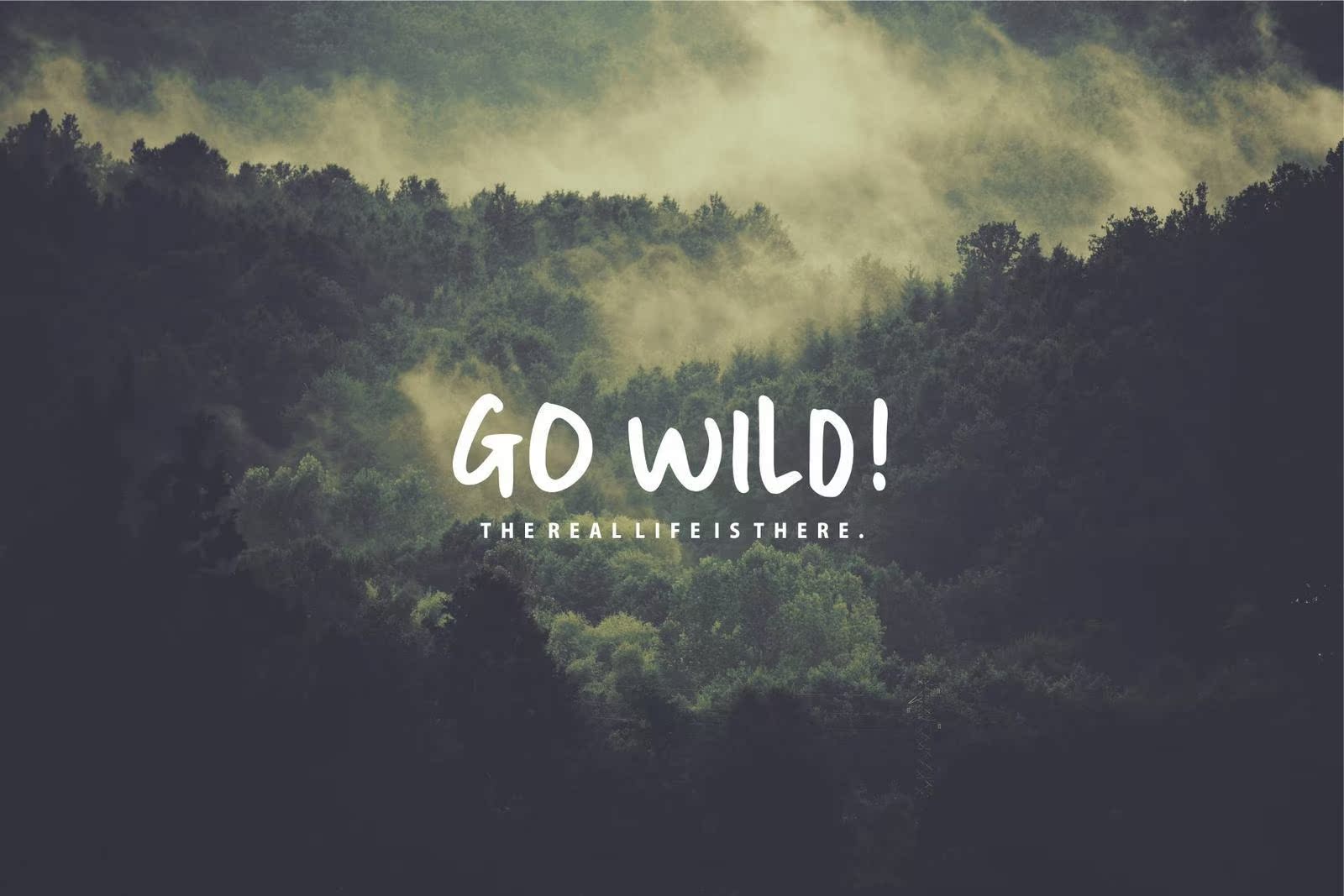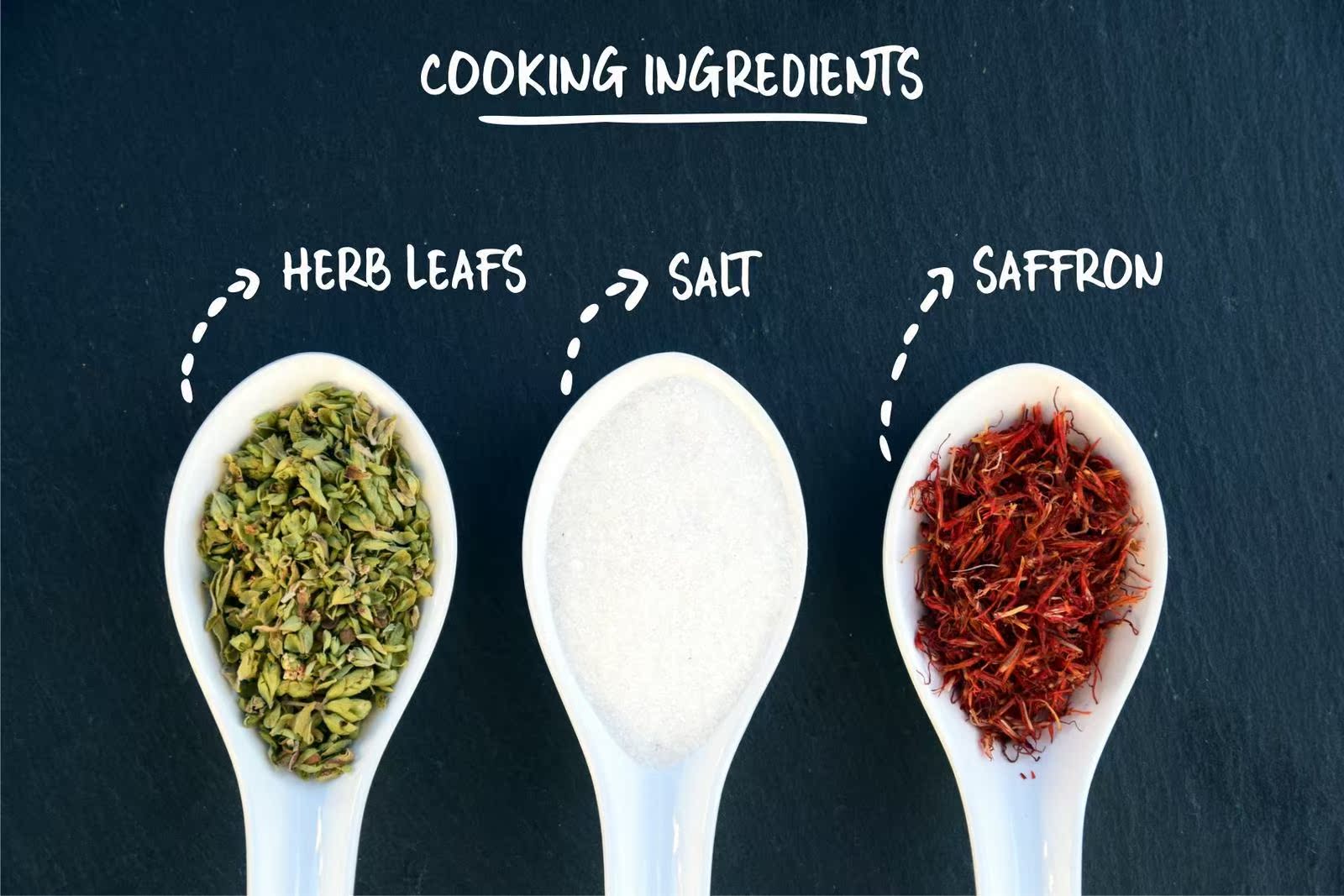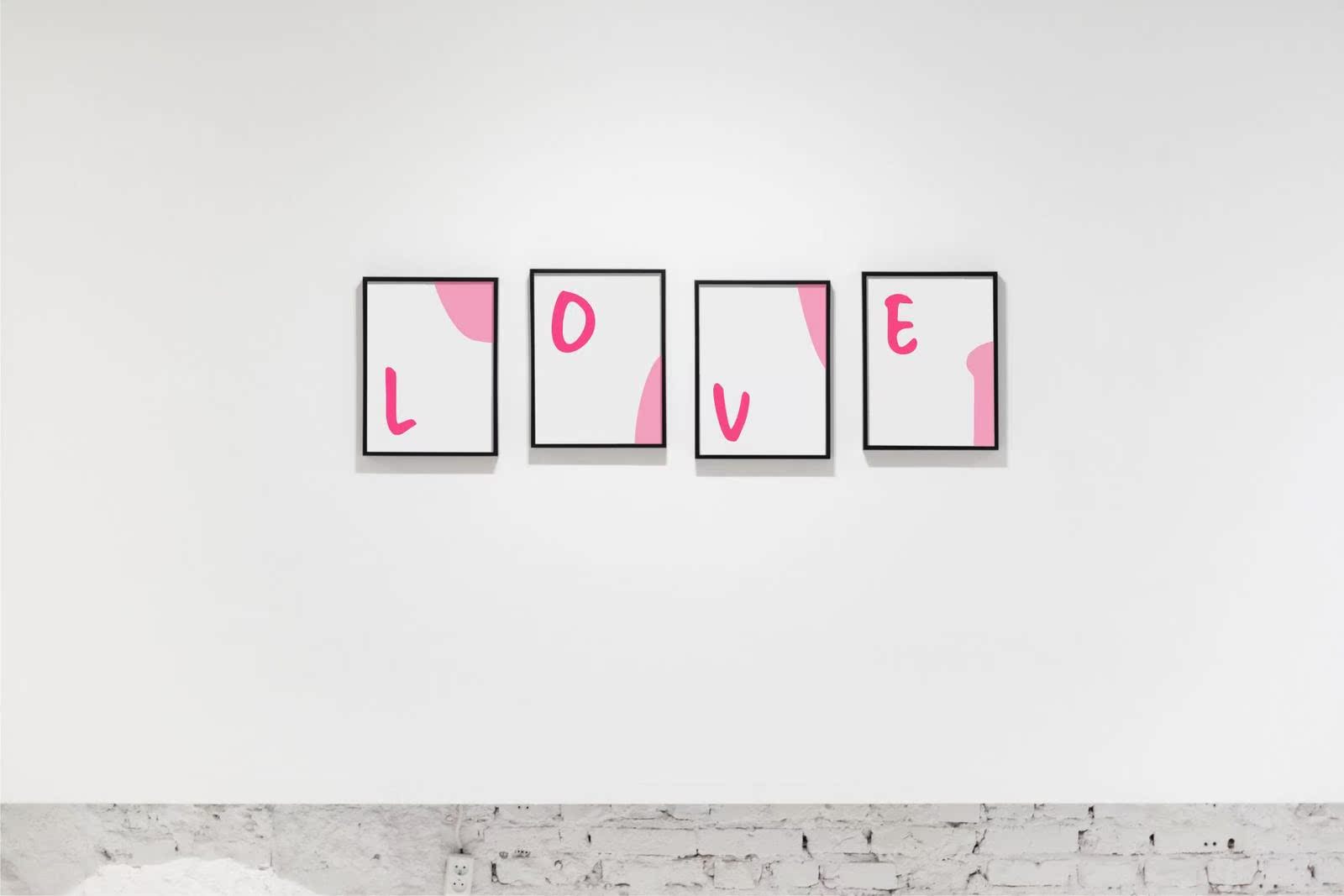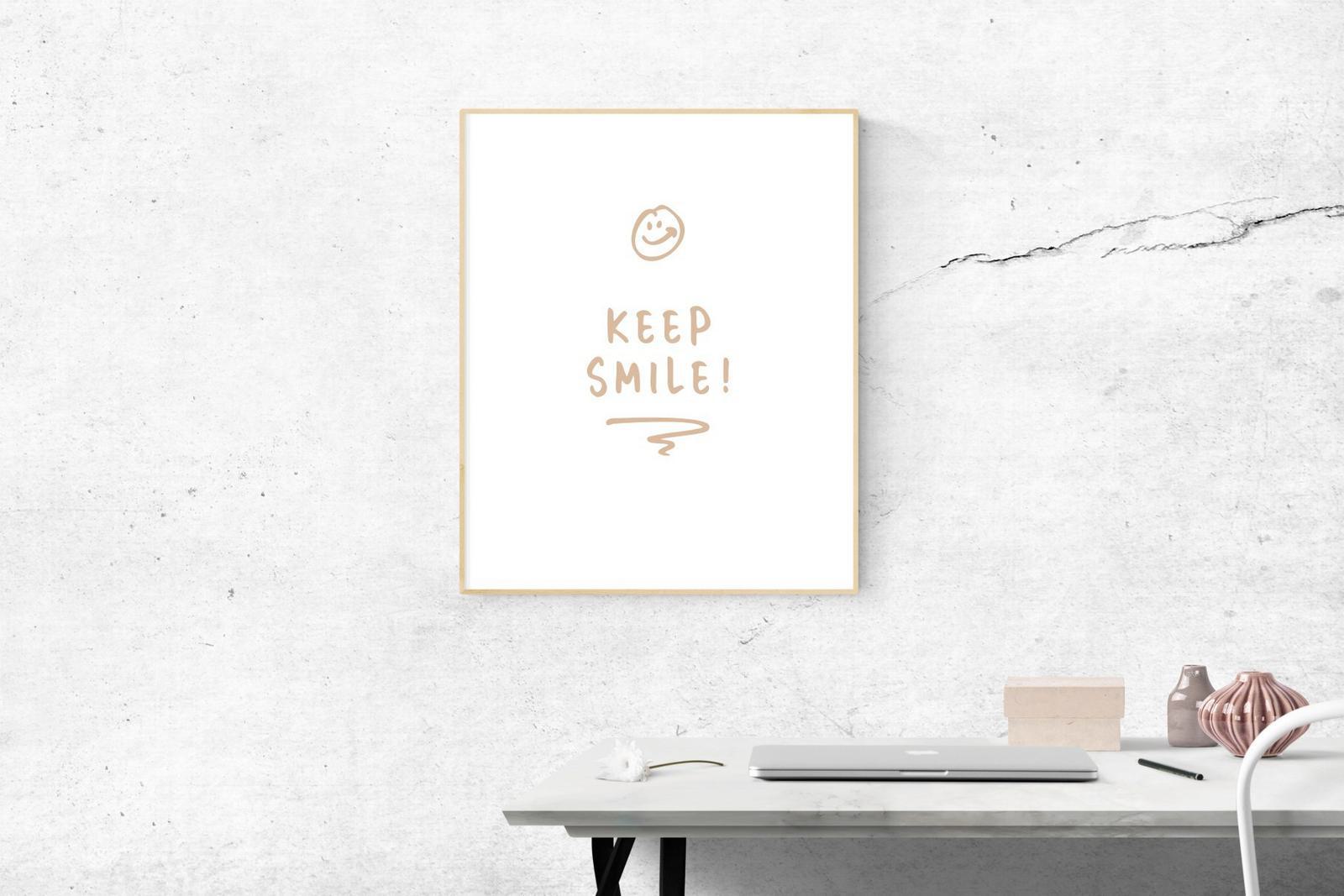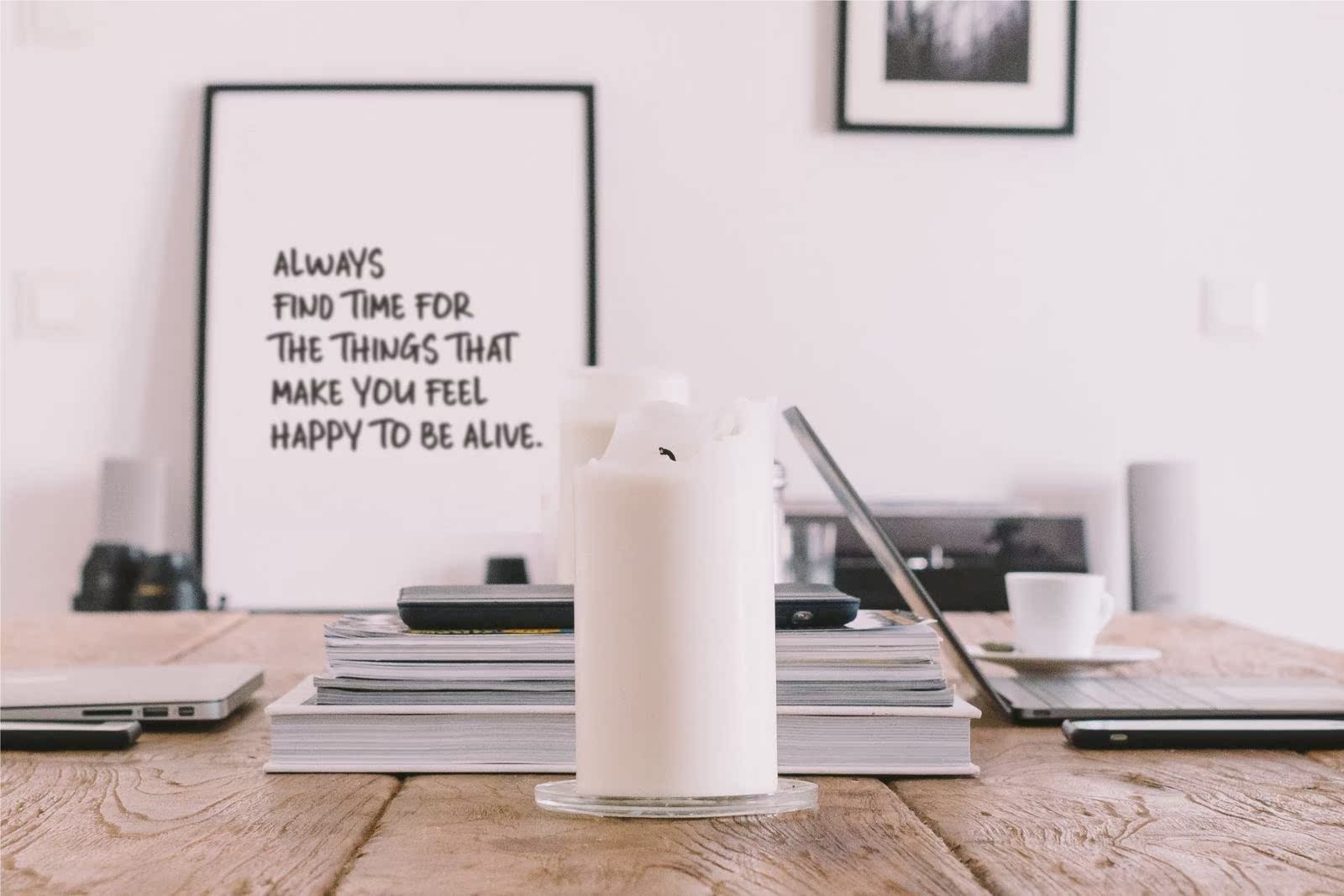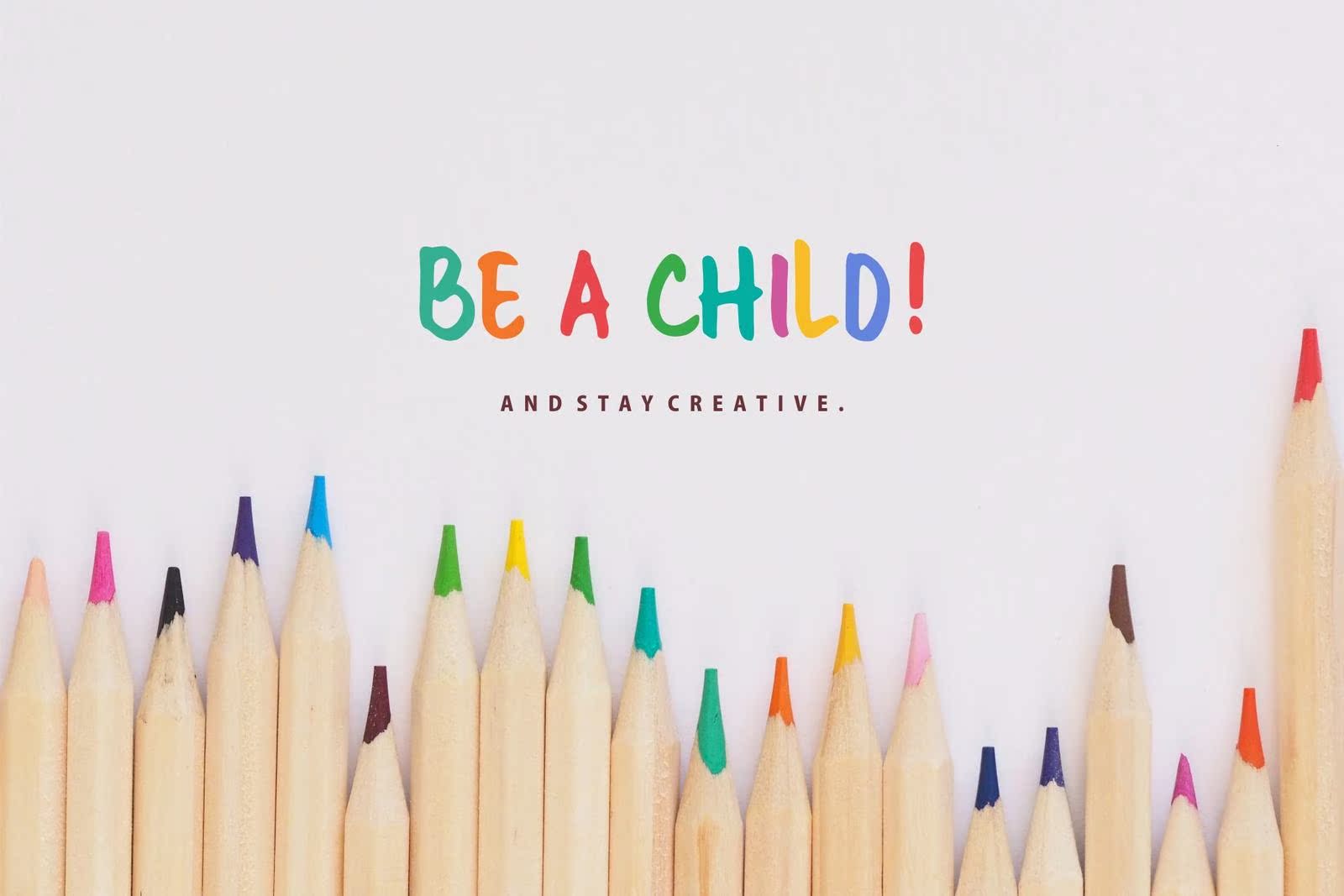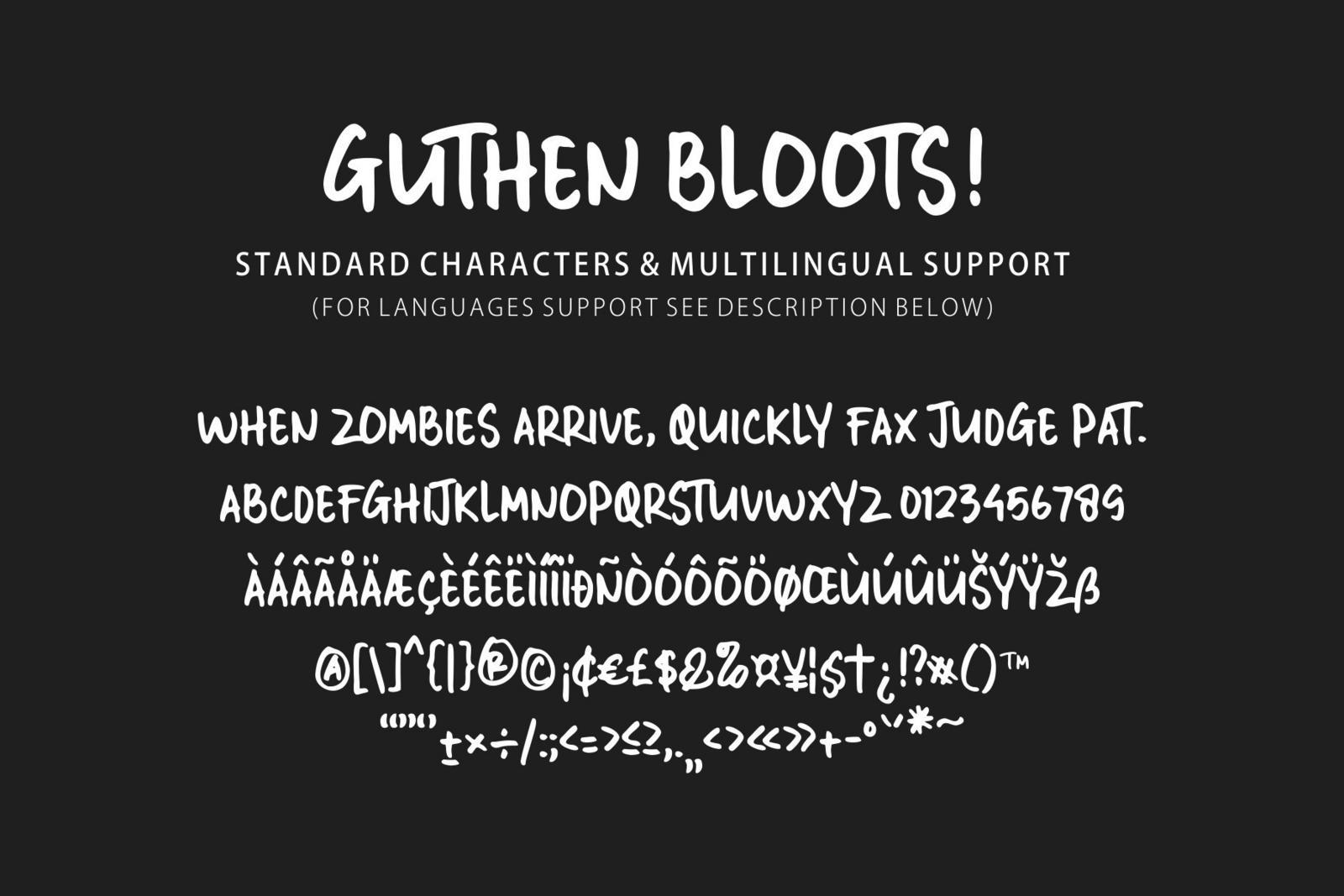
展示我们的血液!此PACKISTATRIALVERSIONOfGhutenbloodsAllCapsByazetype。此版本是Omakea大型项目的最佳选择,外观完美自然!此字体完美地结合了每个角色。您可以根据项目的所有需要使用此字体。每个字体都有自己独特的信息,并且在与其他字体会面时,可以提供动态和令人愉悦的接近度。此字体可以在任何时间和任何项目中使用。您可以在演示文稿中看到图片,它是ooksperfected和legandesign projects。您必须证明!